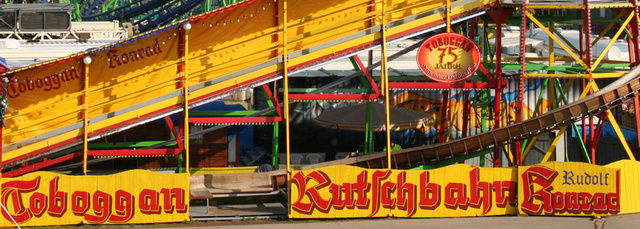
Suche diese Fraktur
kennt jemand vielleicht diese Gebrochene? Alternativ würde mir auch eine Ähnliche weiterhelfen, die aber auch ein „d“ mit so einem senkrechten Hals hat.
Ich hatte gehofft, dass der schräge Schriftzug oben am Förderband die Vorlage für den (eindeutig) gemalten Schriftzug am Zaun gewesen sein könnte.